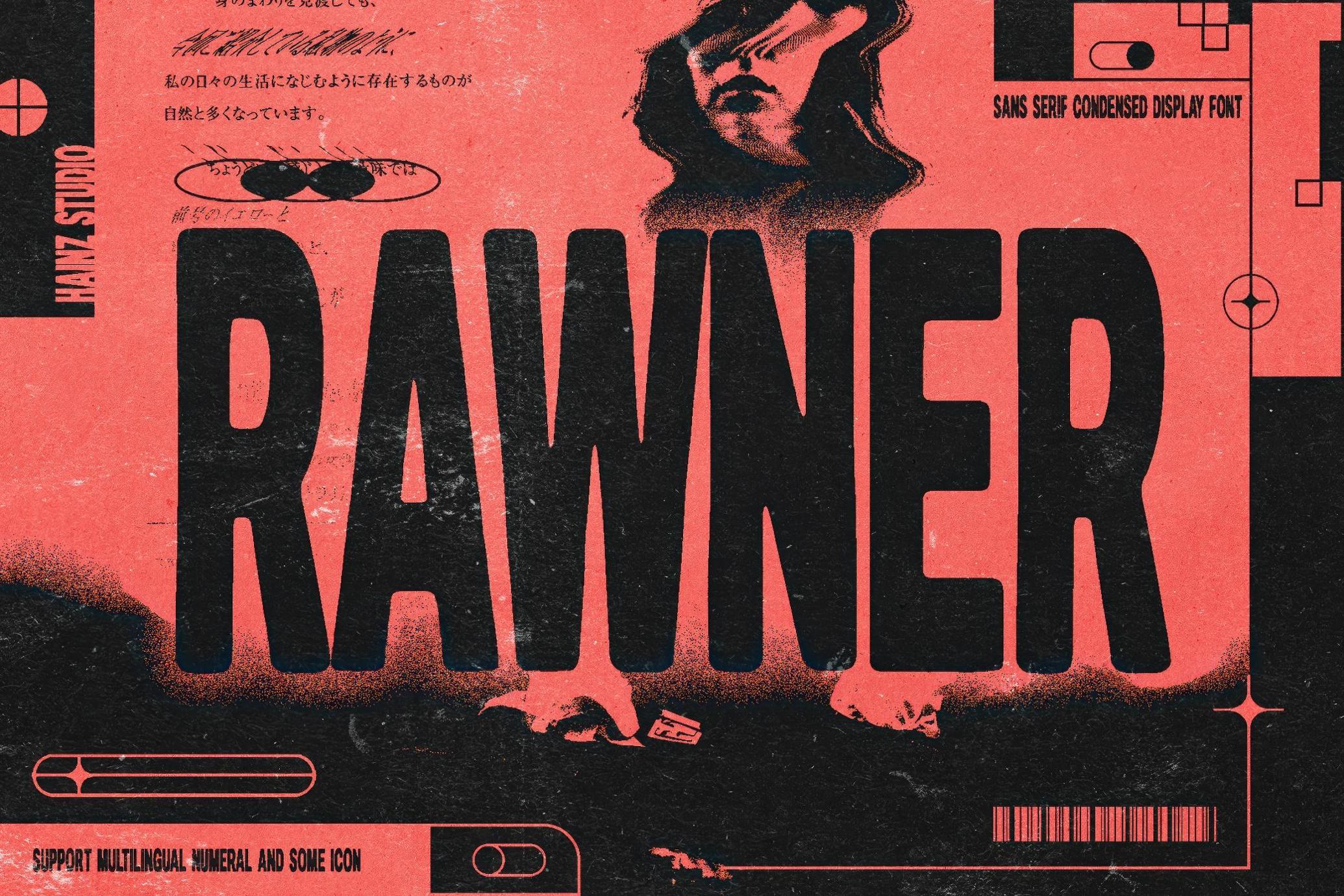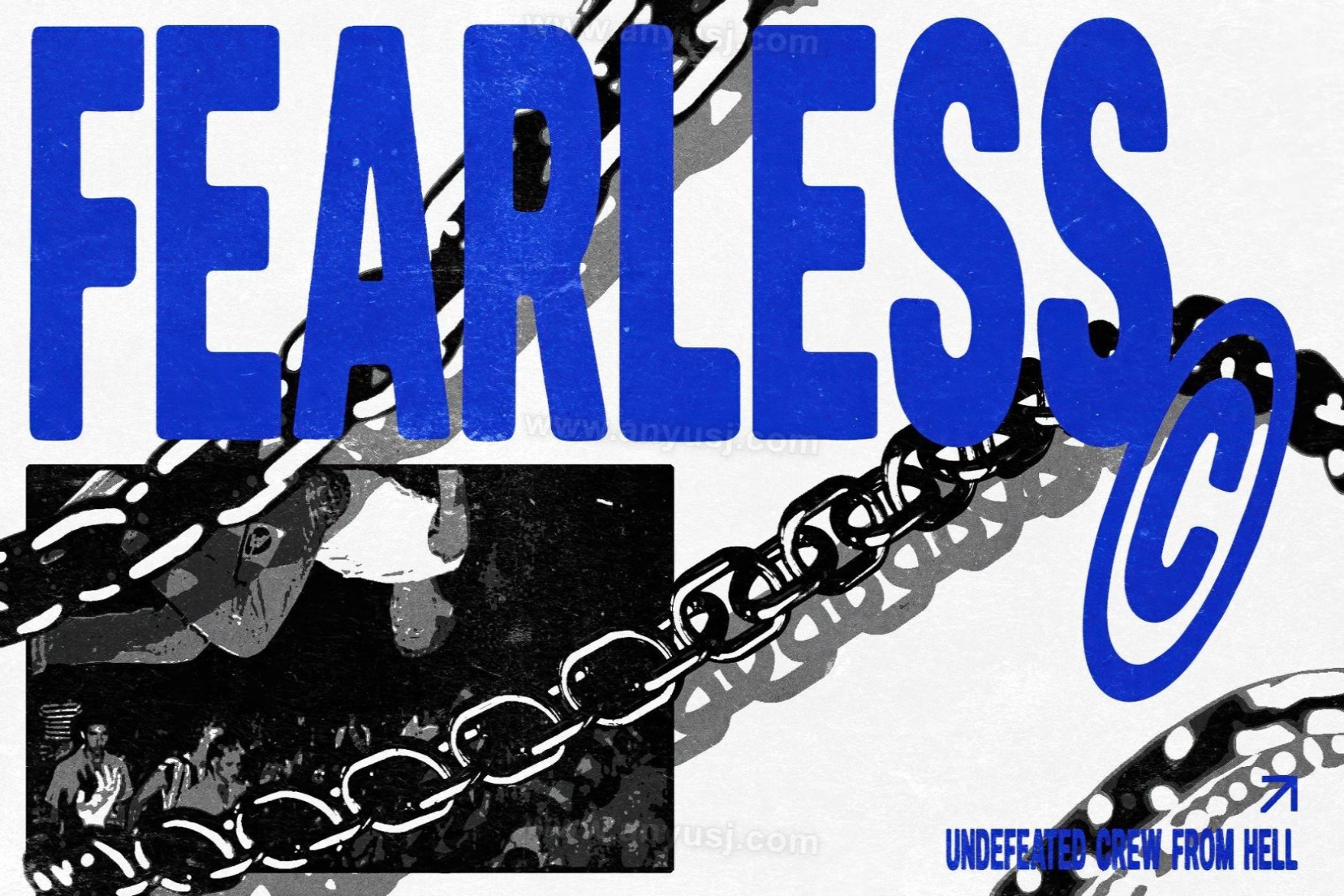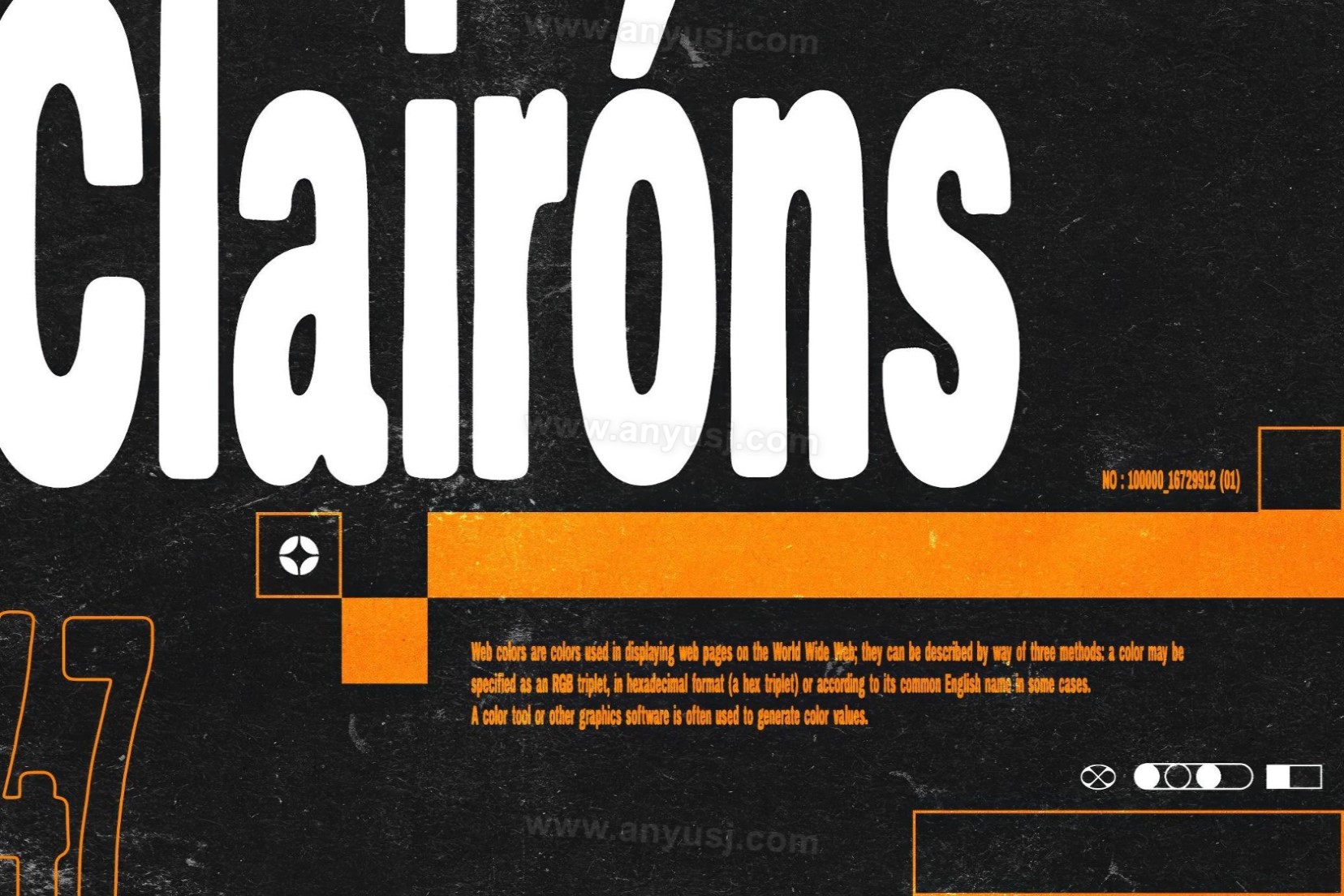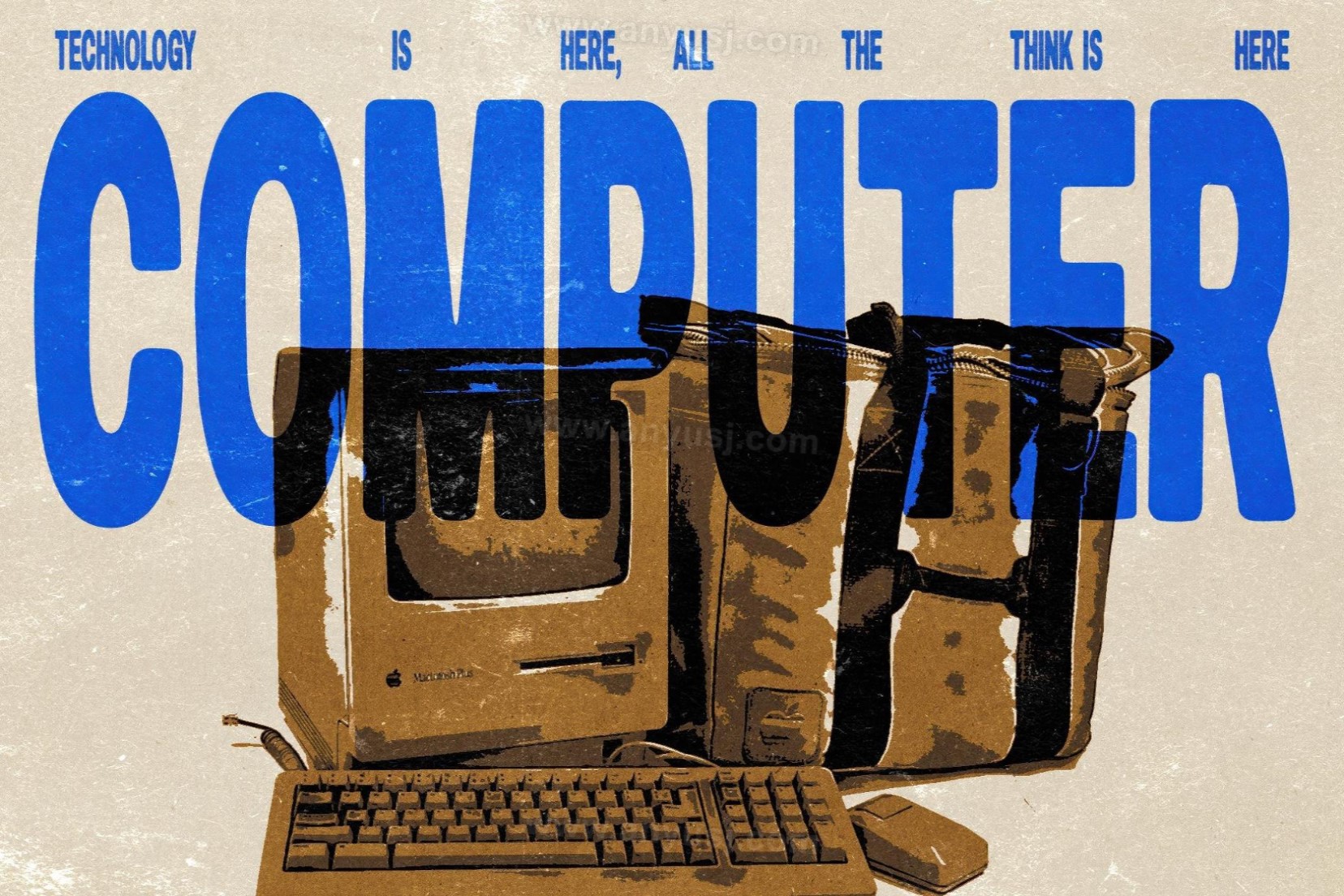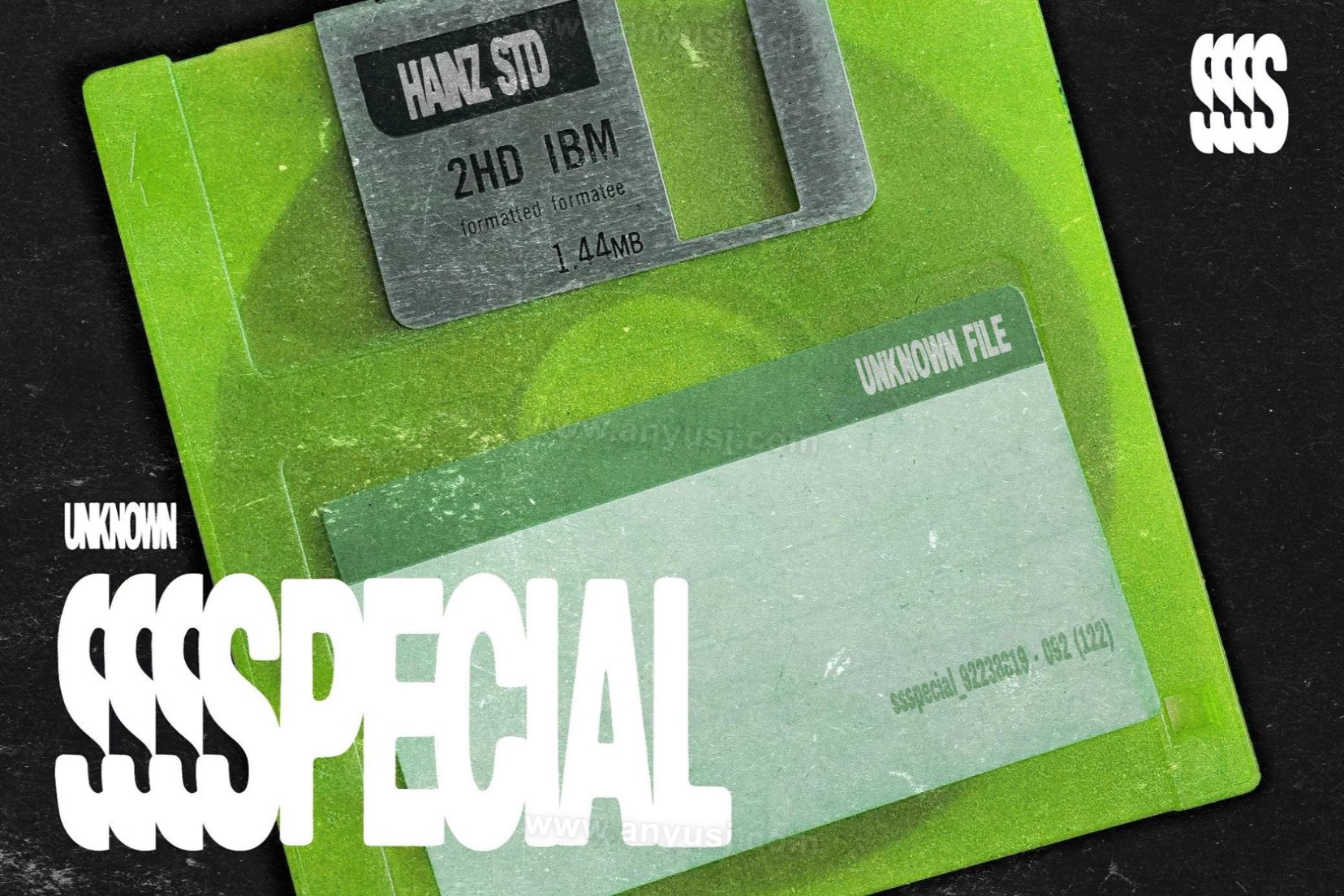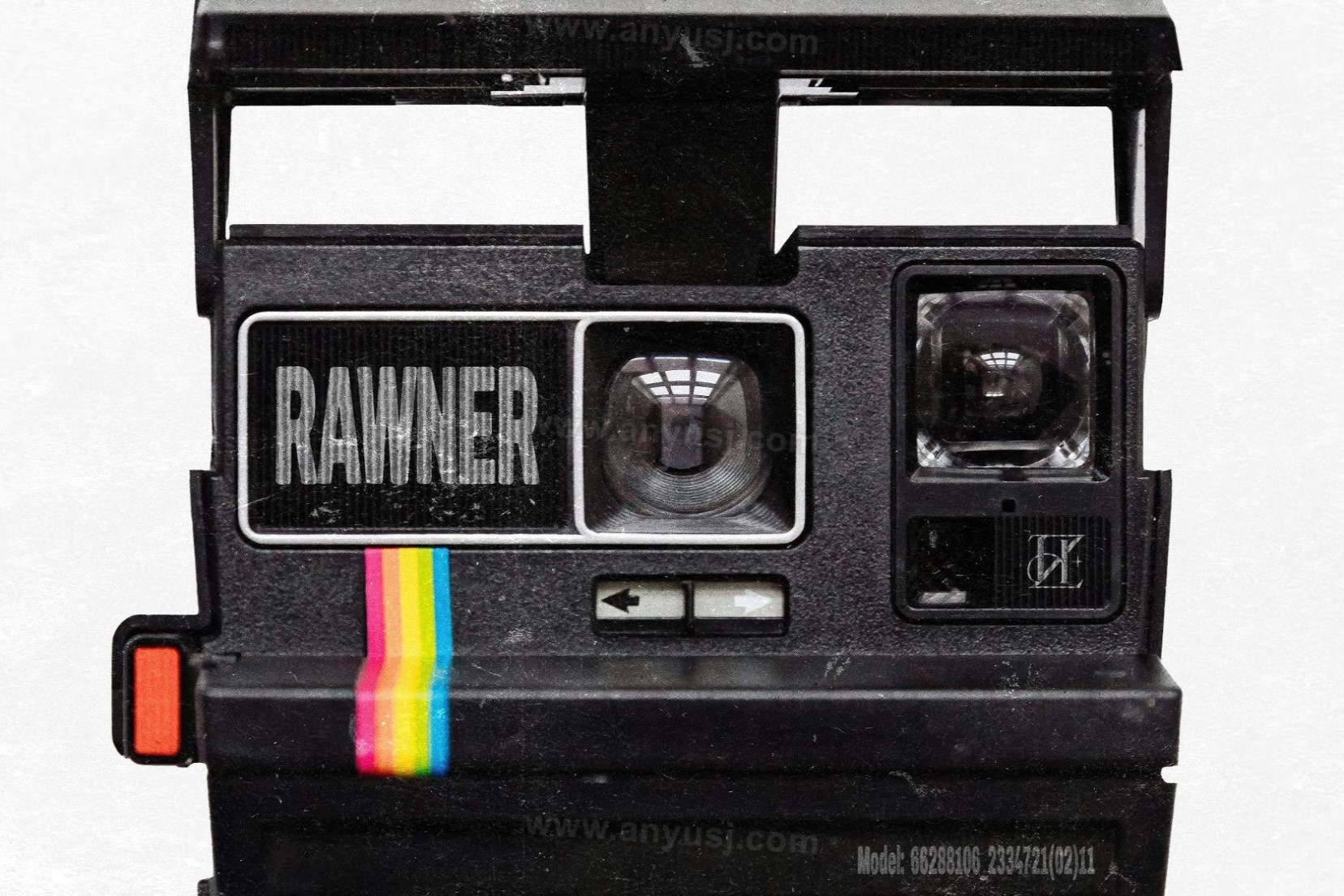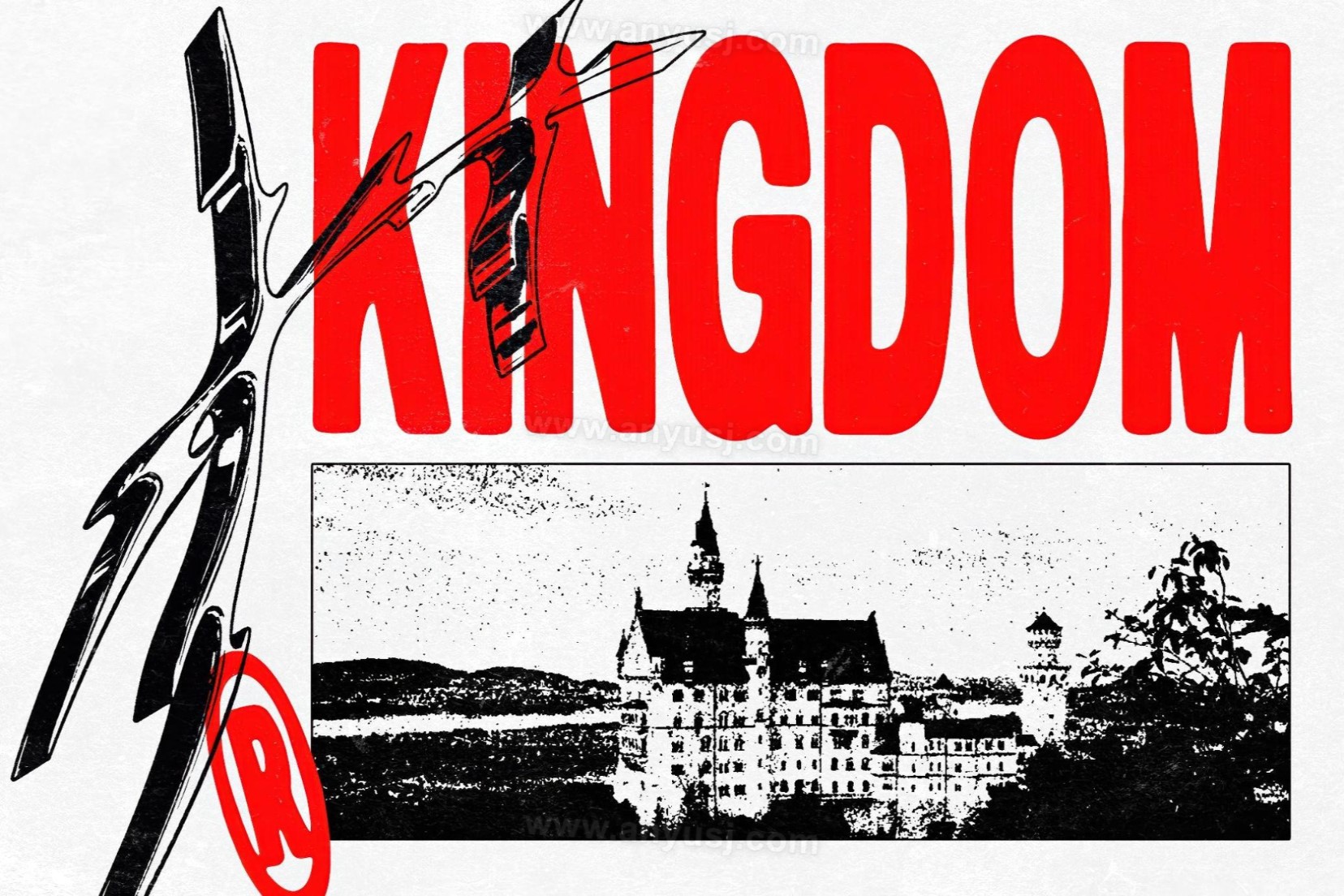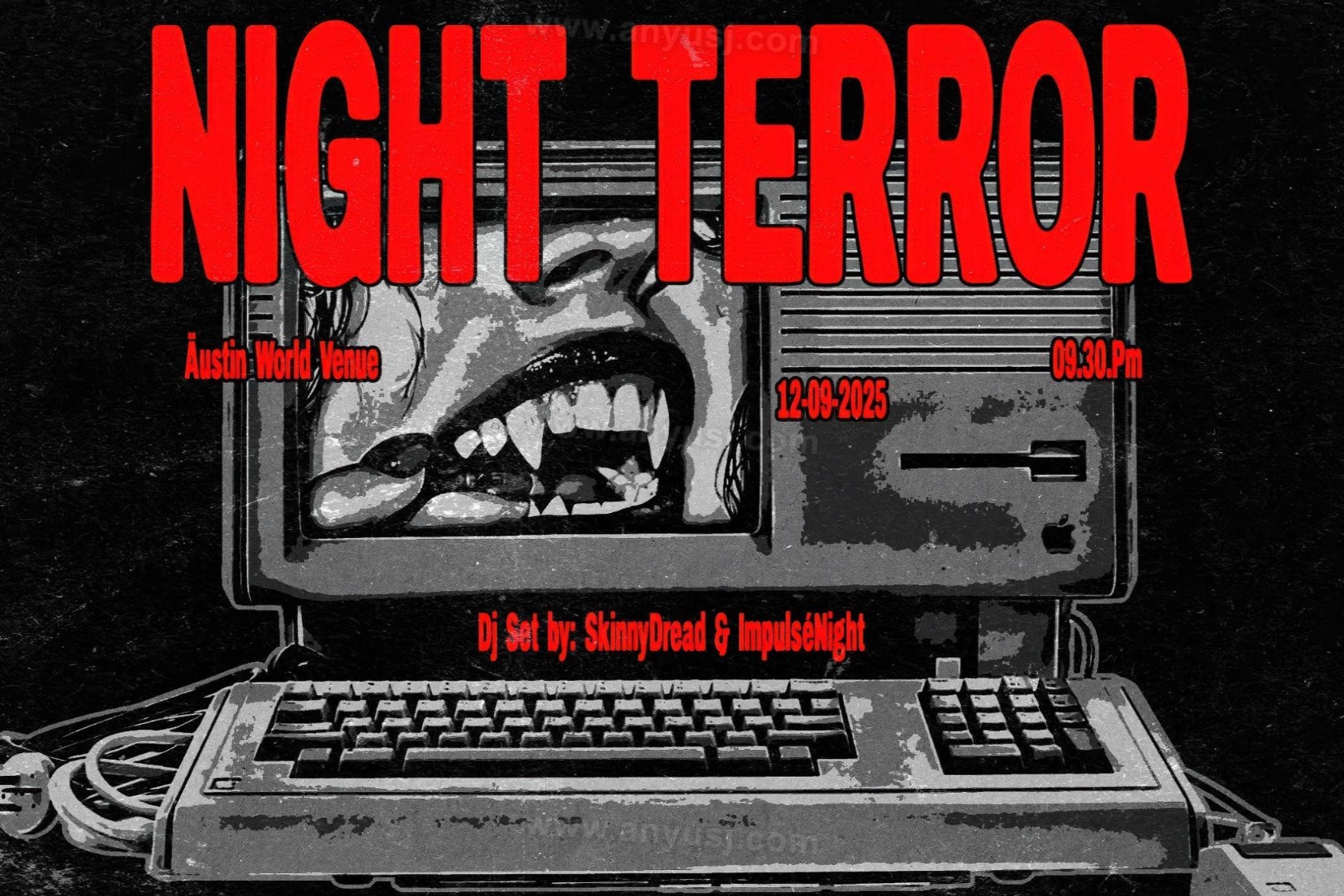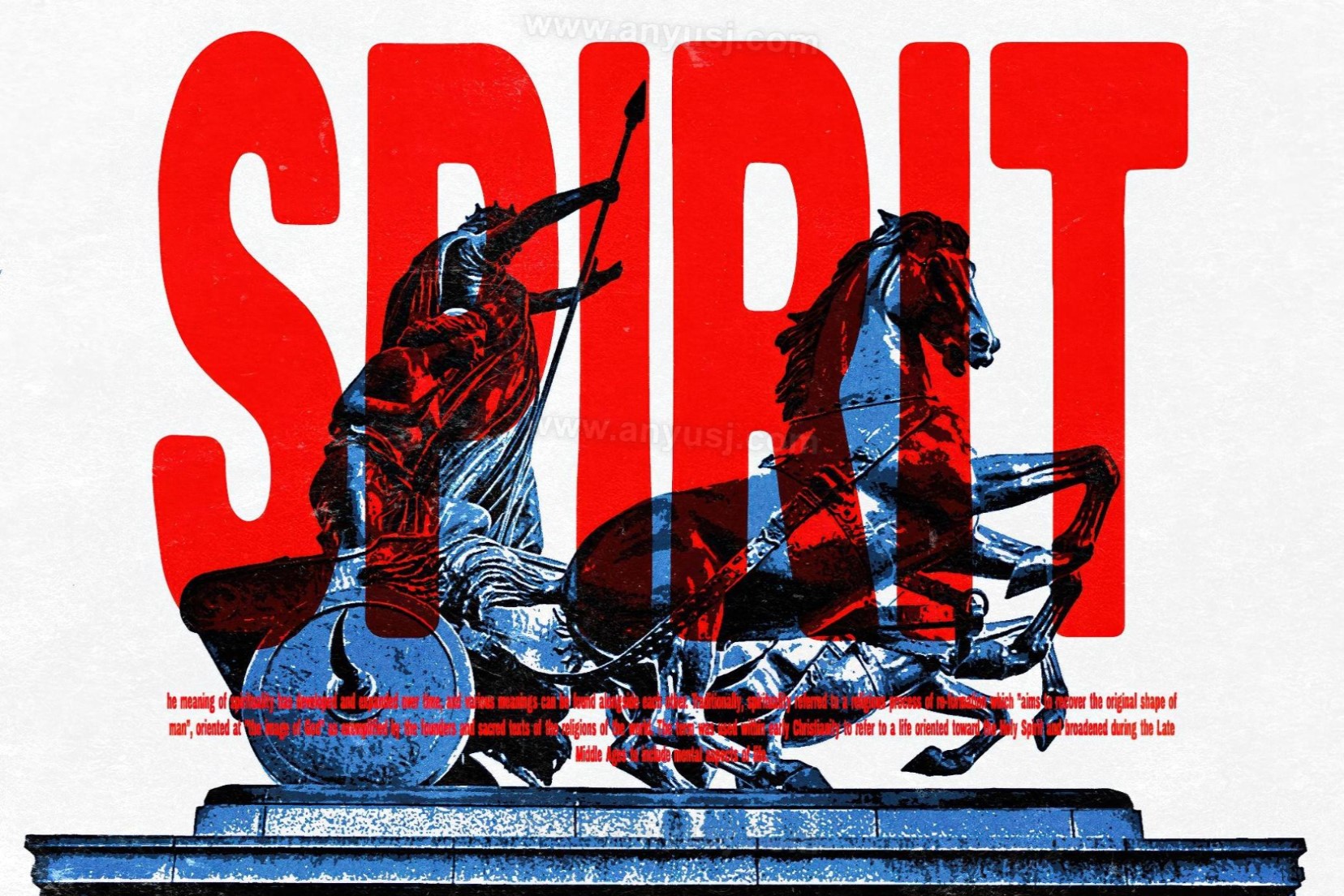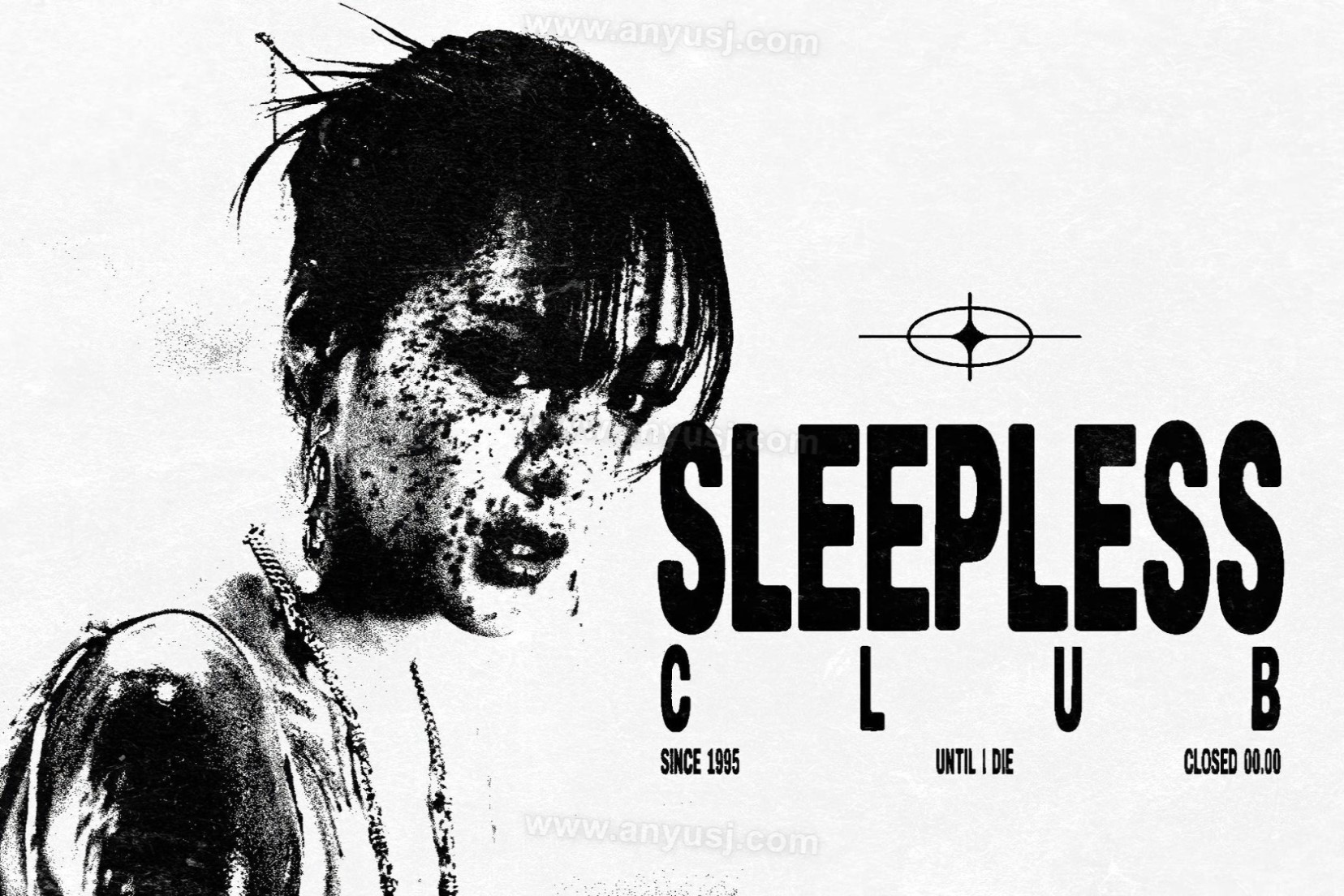
复古摇滚压缩工业风野兽派logo标题排版无衬线西文英文字体Rawner — Condensed Display Font
Rawner 字体是一种压缩的显示,具有块状几何图形和紧凑的间距。它的工业建筑和略带野兽派的结构给人一种可控的紧张感——它看起来像是建在一个带有焊枪和网格尺的仓库里。尽管边缘很硬,但即使在较小的尺寸下,它也能保持清晰易读。提供大写和小写形式,带有数字、多语言支持和基本标点符号。
当您需要大声疾呼地表达观点时,Rawner 效果最好:海报标题、社论副标题、专辑封面、运动品牌、活动传单、标牌以及时尚或音乐领域的任何东西。它还适合在排版锁定中播放,或者与坚韧不拔的纹理、半色调或黑白摄影分层。